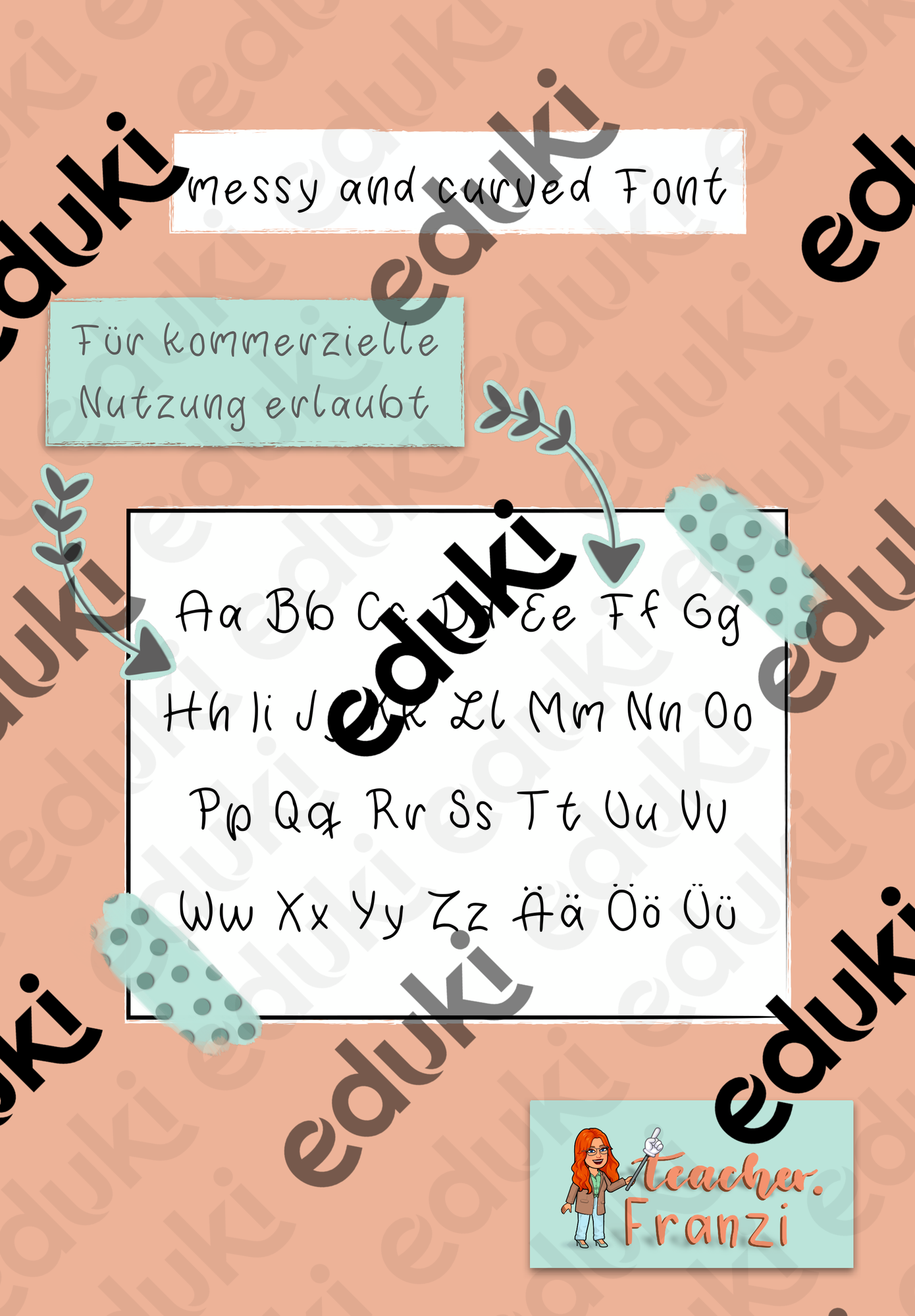
Das Material umfasst eine selbsterstellte Handschrift. Sie ist weder eine Druck-, noch eine Schreibschrift und dient der kreativen Gestaltung.
Die Schrift ist perfekt um deinem Material, deinen Nachrichten uvm. einen individuellen Touch zu geben.
Schriftart: messy and curved font by @teacher.franzi